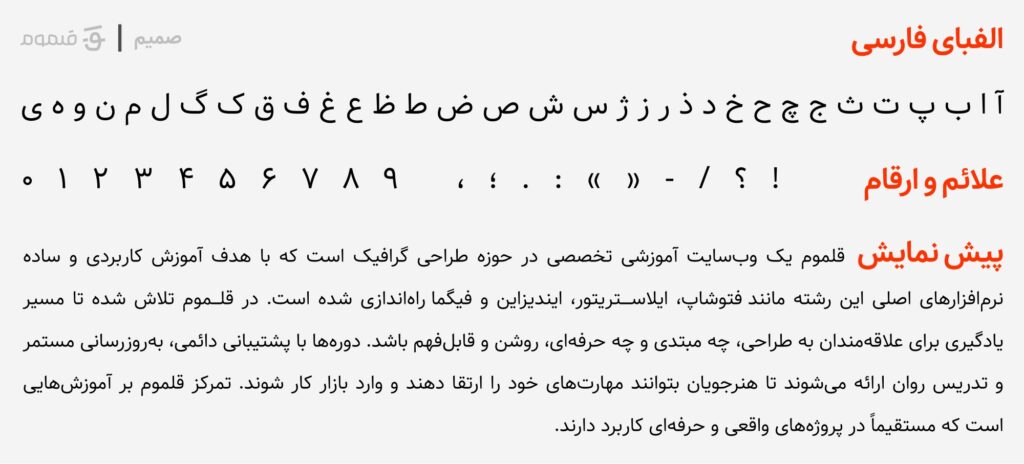
خانواده فونت صمیم
فونت صمیم همانطور که از نامش پیداست، با هدف ایجاد فضایی دوستانه و راحت طراحی شده است. طراحی آن ساده و بدون پیچیدگیهای تزئینی است و همین ویژگی باعث شده برای متنهای طولانی در وب و اپلیکیشنها بسیار مناسب باشد.
این فونت در چند وزن ارائه شده و بهویژه در متون آموزشی و محیطهایی که نیاز به حس تعامل و نزدیکی با مخاطب دارند، عملکرد فوقالعادهای از خود نشان میدهد.